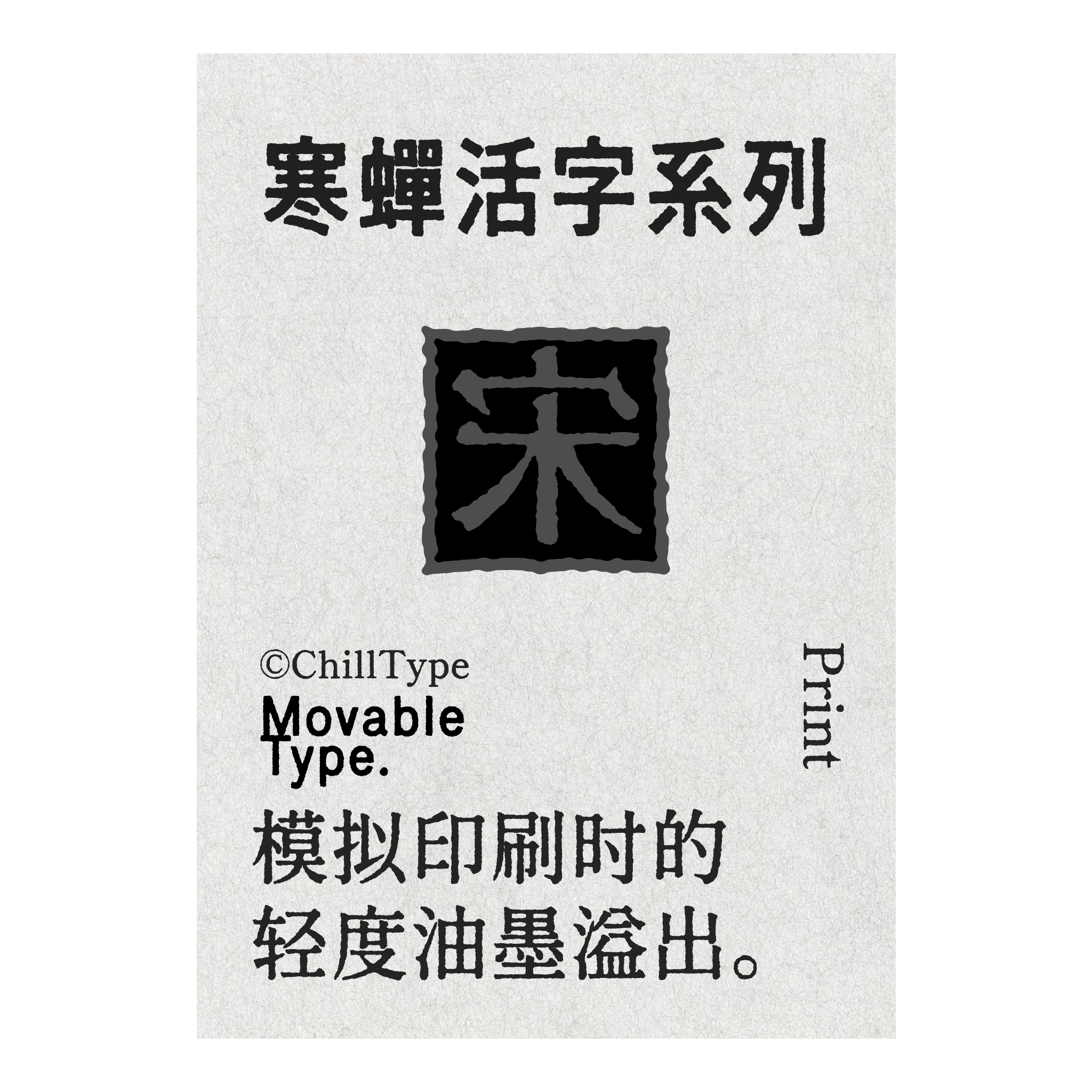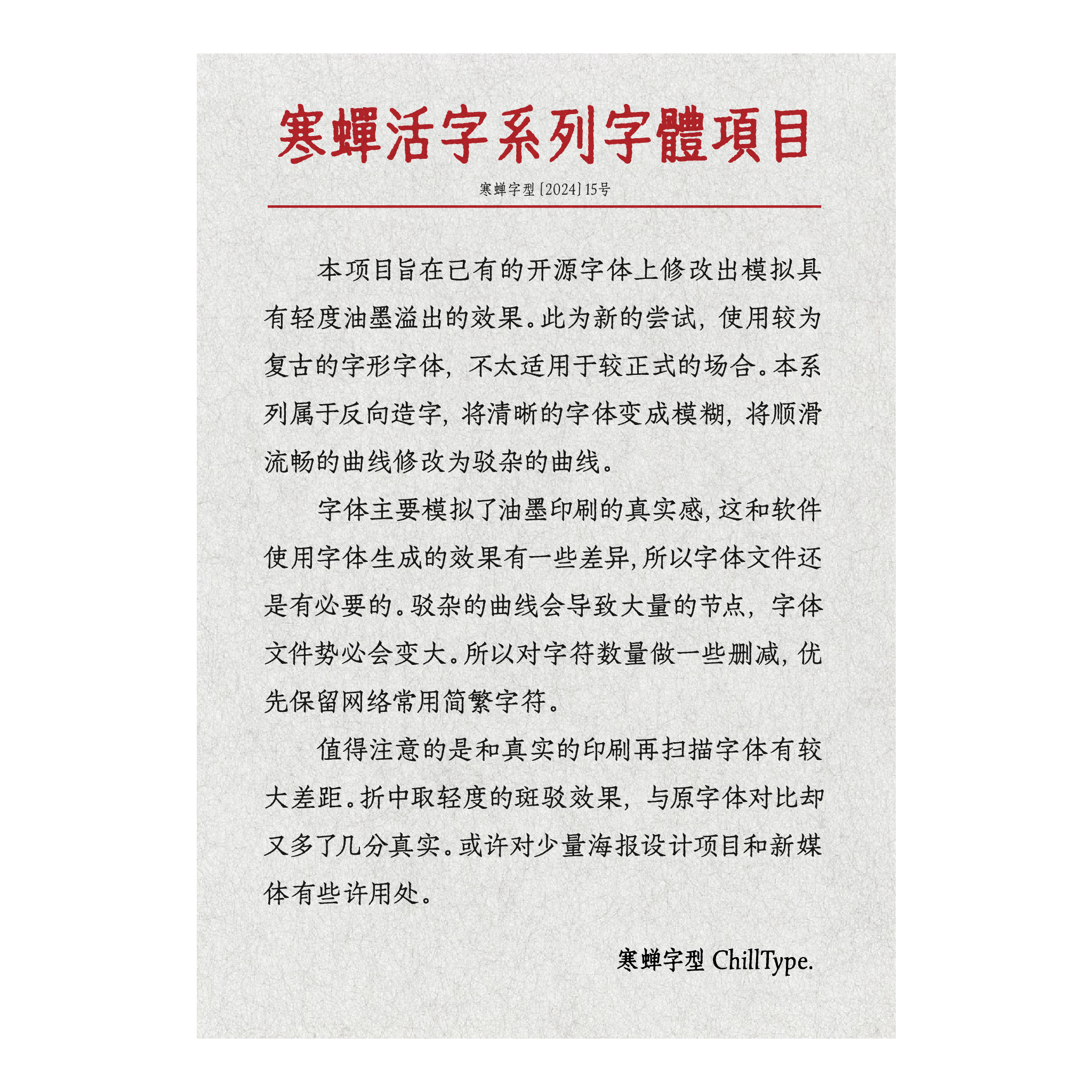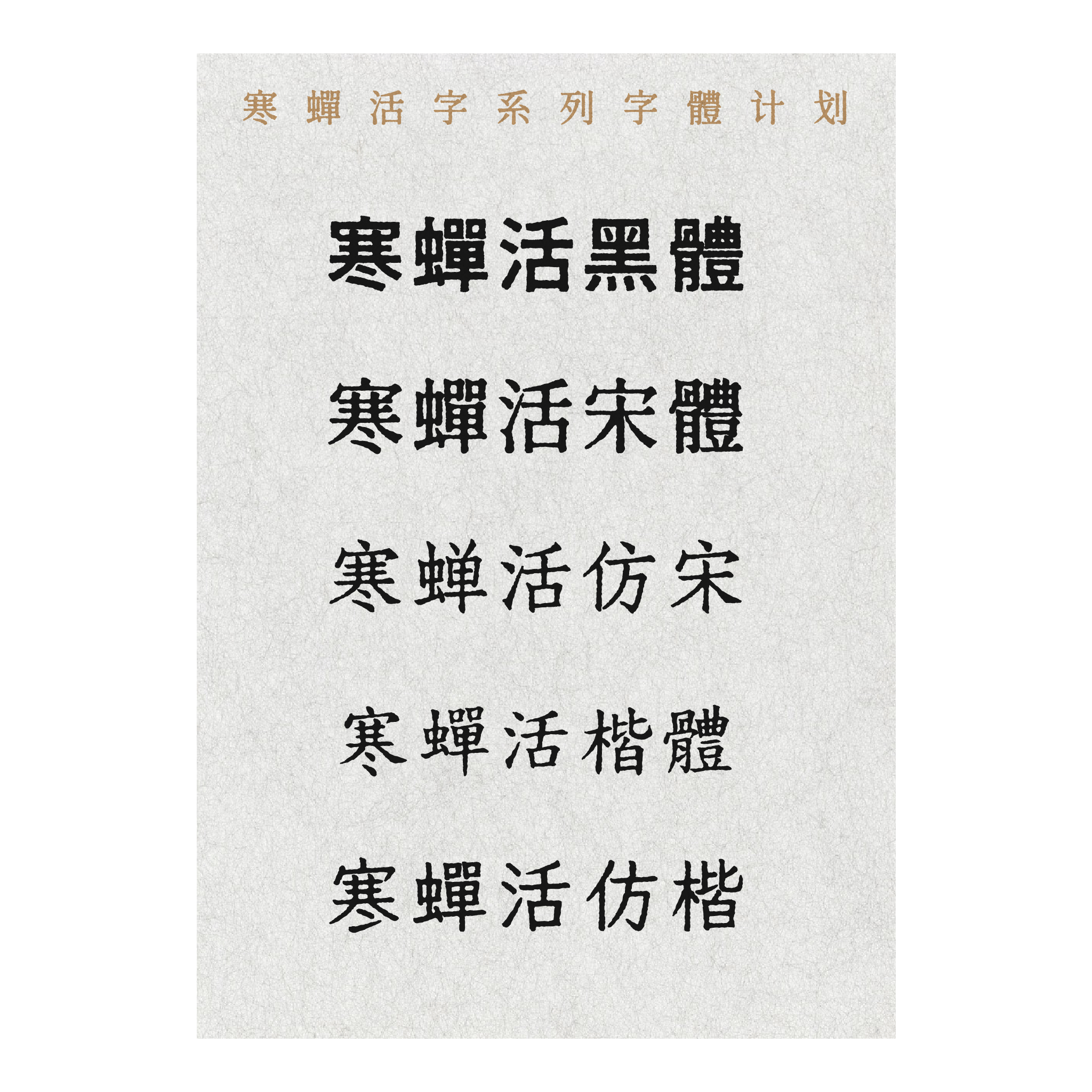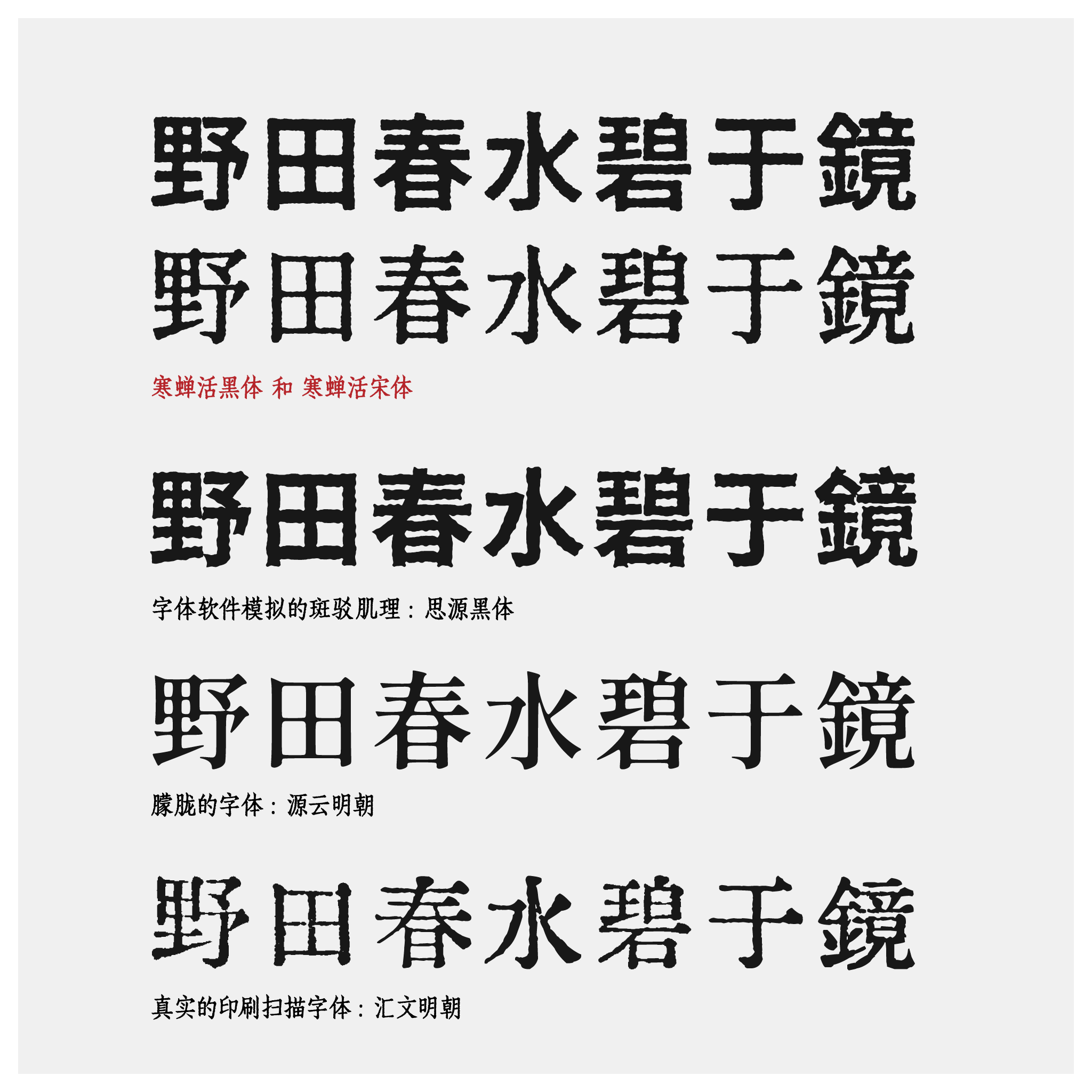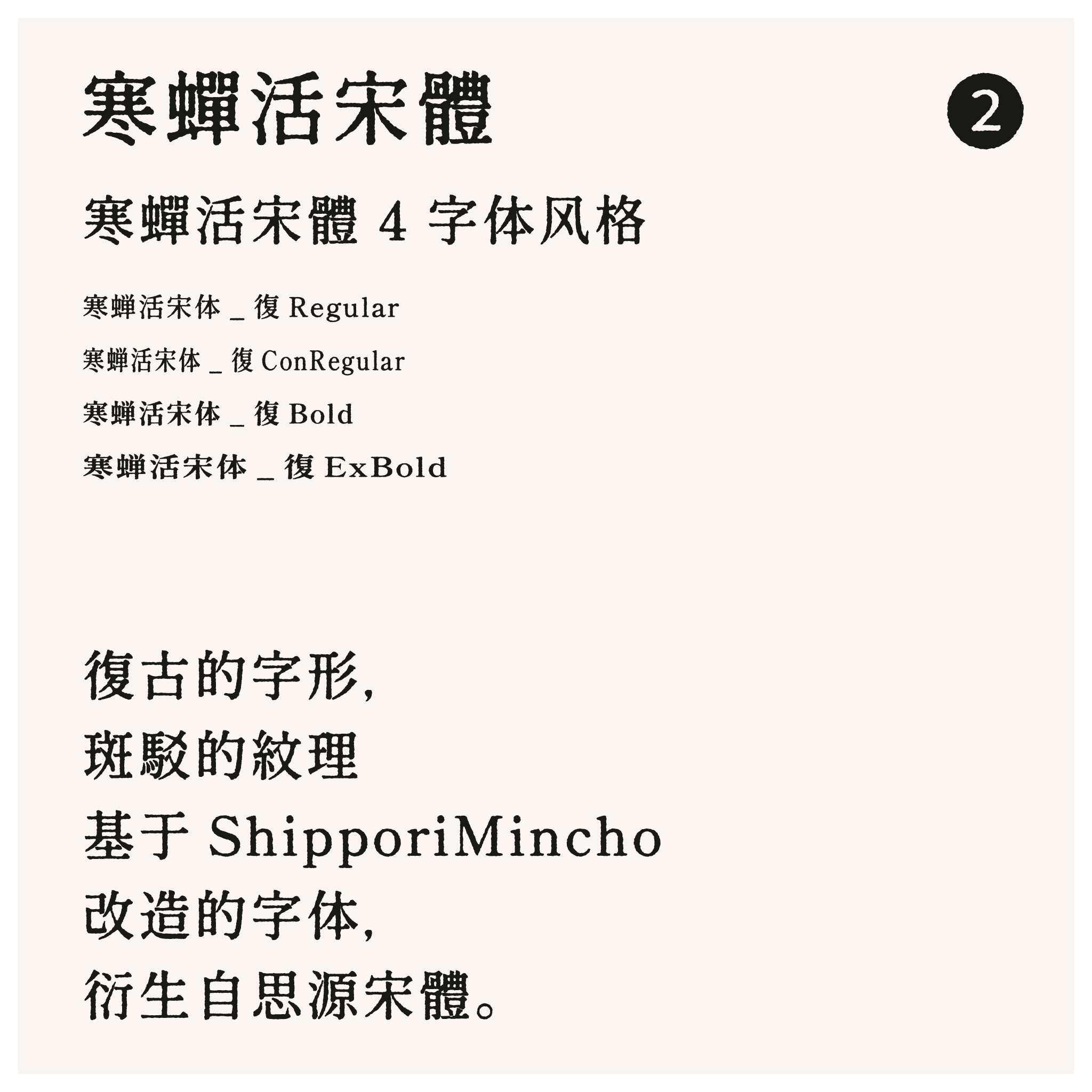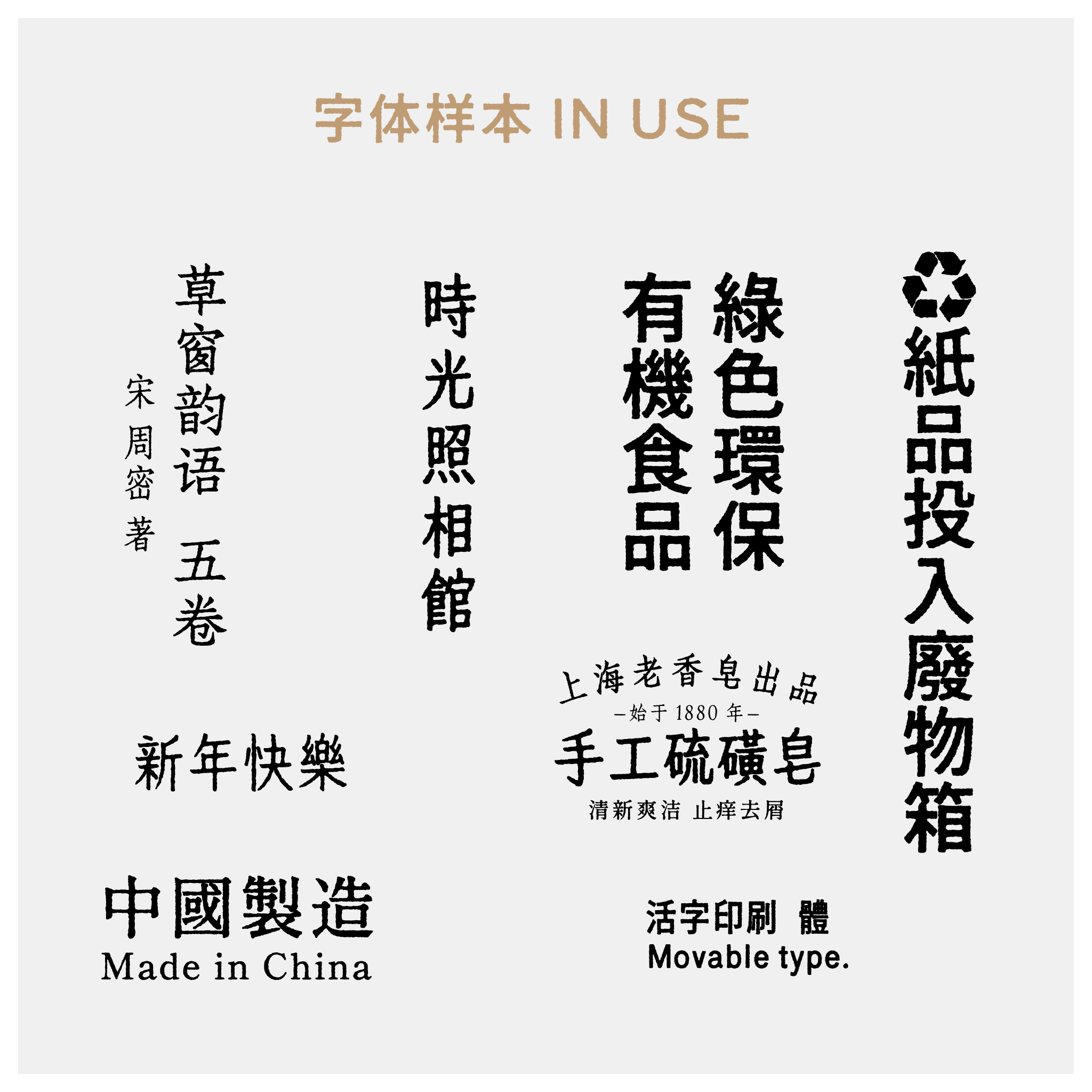
寒蝉活宋体,一款在视觉上散发着浓厚复古韵味的字体,堪称数字时代对传统印刷美学的深情致敬。其字形结构和笔画细节深受传统活版印刷美学的影响,不仅讲究横平竖直中的细微变化,更刻意保留了历史字体中那种略显斑驳的纹理效果。这种斑驳并非瑕疵,而是精心设计的岁月痕迹——它模仿了老式铅活字因长期使用和油墨渗透而在纸张上形成的细微晕染与磨损,让每一笔一画都仿佛承载着光阴流转的故事,增添了温暖的人文气息和手工质感。 这款字体是以日本开源字体 Shippori Mincho 为基础进行深度改造而成,其原始设计已具备精致的日文明朝体风格。而 Shippori Mincho 本身则源自思源宋体(Source Han Serif)这一广受认可的泛 CJK 字体项目,思源宋体为寒蝉活宋体提供了扎实的骨架结构、优秀的跨语言支持以及清晰可读的版式基础。在此基础上,寒蝉活宋体进一步注入了独特的历史质感与艺术个性,使其在现代屏幕或印刷品上既能保证良好的可读性,又能瞬间营造出一种怀旧、典雅且富有文化沉淀的视觉氛围,非常适合用于书籍标题、品牌标识、复古海报或任何需要突出传统工艺美感的场景。